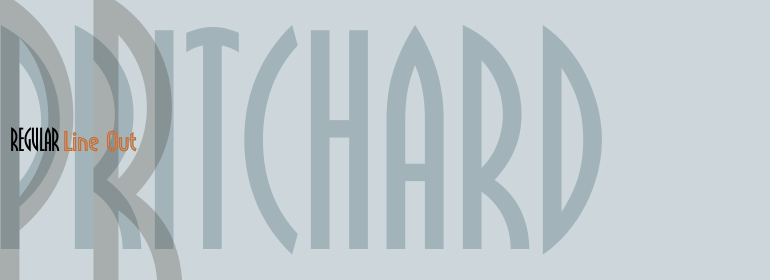
Pritchard™
Pritchard™,这款字体结构工整、笔画清晰,兼顾美观与易读性,适用于标题、正文、海报、包装、LOGO 等多种场景。字形优雅稳定,风格百搭耐看,适配日常排版与创意设计,让文字呈现更舒适、更具质感。Pritchard™一笔一画,皆是细节,以均衡的比例、流畅的线条打造舒适视觉体验,字形端正大气,风格简约现代。无论是商业设计、品牌宣传还是日常排版,都能轻松驾驭,让文字更有格调与力量。Pritchard™字体下载。